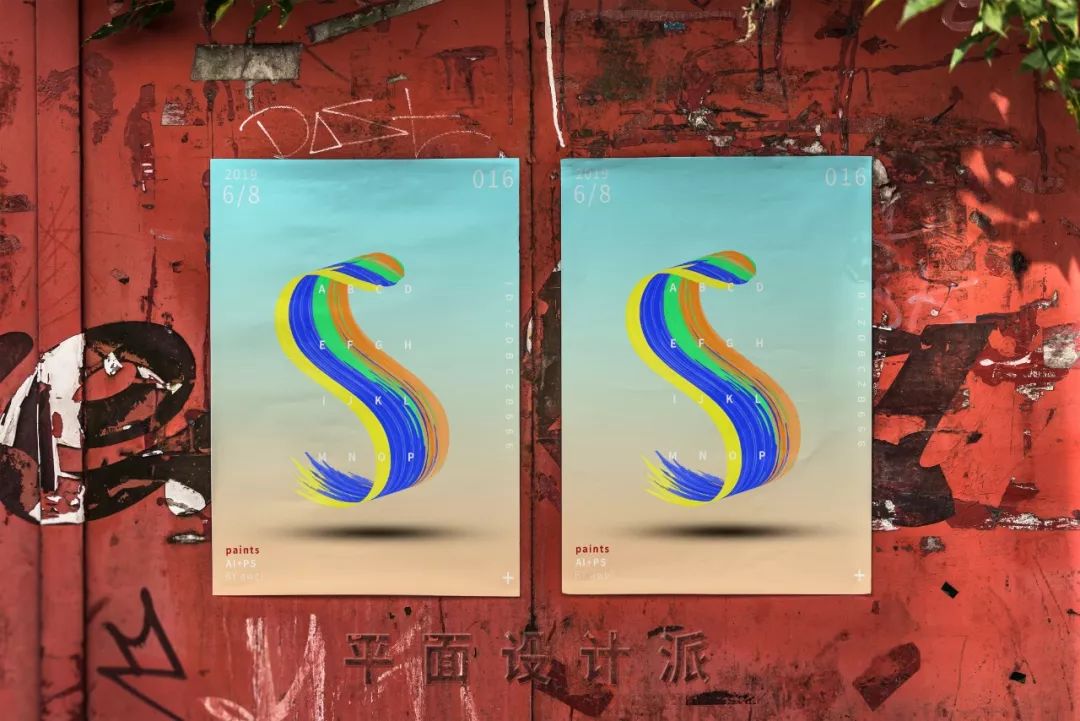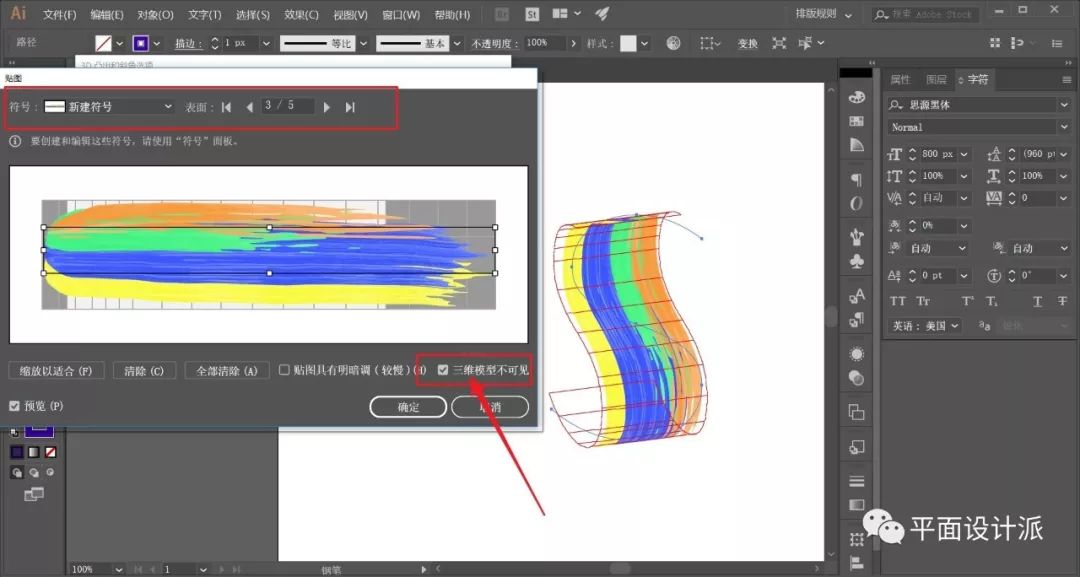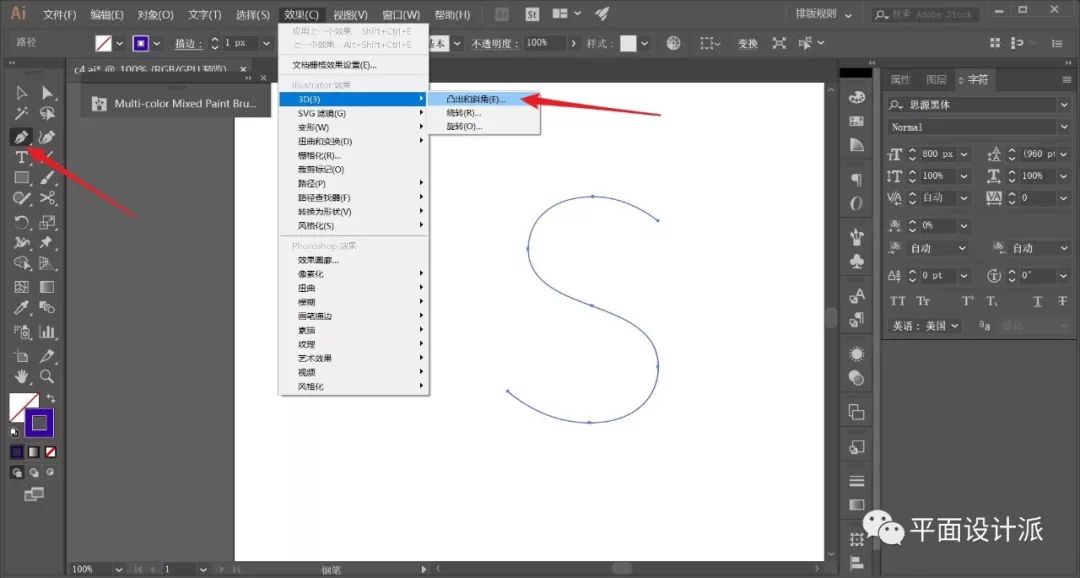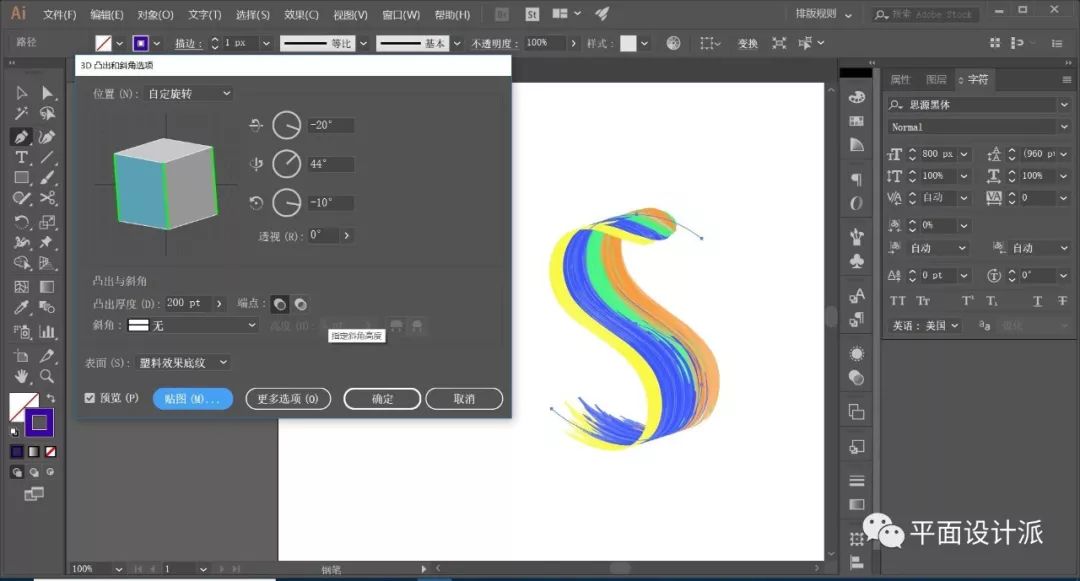
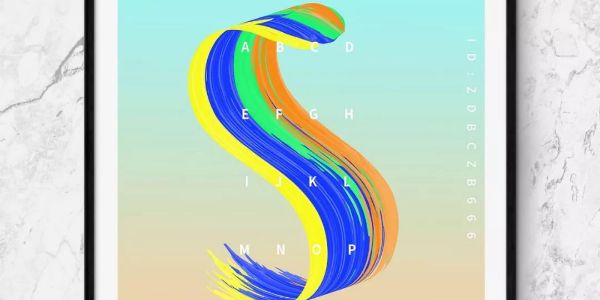
如何用AI做出那种火爆的立体油漆字!
在文章开始之前,我们先来说说怎么载入ai笔刷。
首先,打开ai,我随意地新建画布,给个深色填充,方便观看:
打开画笔面板,执行其他库—打开画笔,如图所示:
在桌面找到笔刷文件,如图所示:
就这样我们顺利地导入了ai笔刷,一共为大家提供26种样式的笔刷:
选择画笔工具,关掉填充色,修改描边色。在画布上随意涂抹,即可得到类似油漆的效果:
现在我们再新建海报大小的画布。
选择一款笔刷样式,描边色设置为蓝色,画出一条直线,得到如图的效果:
照着这样的方法,得到多条油漆样式直线,并适当重叠它们,以此得到油漆效果,如图的样式,全选编组:
(注:必须是直线,因为方便后续贴图。可以钢笔/直线工具画出直线,用笔刷替换,这我就不多解释了)
打开符号面板,将其拖入:
选择钢笔工具,描出“S"路径。执行效果—3D—凸出和斜角:
适当调整朝向及凸出厚度,如图所示:
点击贴图,除了侧面不贴图,其余面都贴图。切记,一定要勾选上三维模型不可见,这是呈现效果的关键,如图:
适当调整笔刷符号大小,尽力得到完美的效果,如图的效果就像是连续的一样:
可以再适当调整方向,以此得到更好的效果:
得到效果后,进行一次扩展外观:
现在我们打开ps软件,拉个渐变作为背景色,托人对象:
最后,适当排字码板,调下色:
导入海报样机,看看效果: